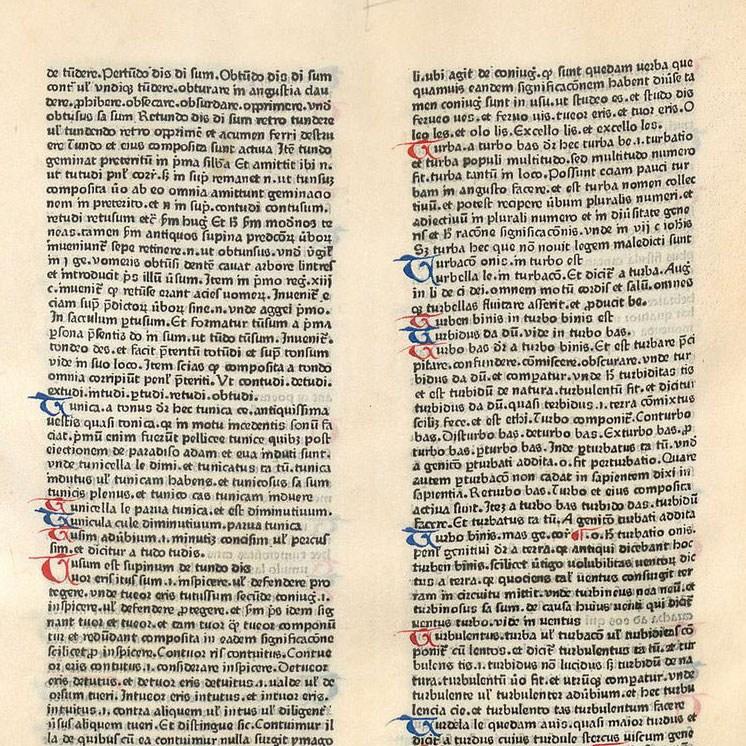
Ein klassischer Manuskripthalter für den Handsatz bestand aus einem Tenakel und einem Divisorium. Das Tenakel war ein Stück Holz, das über einen Metall-Sporn, einer Klemme oder einer Schraube am Setzkasten befestigt werden konnte.
Das Divisorium war ursprünglich eine Holzgabel, die entlang des Tenakels nach oben und unten geführt werden konnte.
Ein Durchbruch gelang dem Uhrmacher Ottmar Mergenthaler. Seine erste Maschine mit dem Namen »Blower« wird 1886 vorgestellt und kein geringerer als Thomas A. Edison bezeichnete sie ohne zu zögern als 8. Weltwunder. Zum Setzen des Textes bedient man sich bei dieser Maschine einer Art Schreibmaschinentastatur. Betätigt man eine Taste, wird eine so genannte Matrize – eine Gussform des Buchstabens – aus einem Magazin freigegeben. Der Setzer gibt nun so lange weitere Matrizen frei, bis eine Zeile gefüllt ist. Die komplette Zeile wird anschließend auf einmal gegossen und aus der Maschine ausgegeben. Dieses Prinzip gab der Maschine auch ihren Namen: A Line of Type (Eine Zeile Schrift). Kurz: Linotype. Die nach dem Guss nicht mehr benötigten Matrizen werden vollautomatisch in das Magazin zurückgeführt. Man kann somit ununterbrochen setzen und gießen und die Satzleistung eines geübten Setzers steigert sich durch diese Maschine auf circa 6000 Zeichen pro Stunde.
In Konkurrenz zur Linotype-Maschine wurde 1897 von Tolbert Lanston die Monotype entwickelt. Der Satz wird hier auf zwei Maschinen (und Berufe) aufgeteilt. Der Taster "setzt" auf dem "Taster", indem er ein papiernes Lochband "beschreibt". Dieser Lochstreifen steuert dann die Gießmaschine, die den Satz ausgibt: als korrekturfertige Kolumne aus Einzellettern (»Mono Type«) zusammengesetzt. So können eventuelle Tippfehler auch nach dem Guss noch leicht korrigiert werden. Es können auf einer Monotype-Gießmaschine aber auch Einzellettern zur Verwendung für Korrekturen oder den Handsatz gegossen werden. Es gab verschiedene Gießmaschinen für verschiedene Schriftgrößen. Die Monotype zeichnete sich durch eine bessere Qualität in der Zurichtung der Buchstabenpaare (am Computer Kerning genannt) und konnte auch größere Grade gießen (Linotype in der Grundausstattung nur bis 12p), brauchte aber mehr Platz, zwei verschiedene Spezialisten (Taster und Gießer), war im Betrieb deshalb teurer und die Matrizen konnten zeitweise/teilweise von der Monotype Corporation nur gemietet/geliehen werden.
Deshalb war die Linotype vorwiegend in kleinen und mittleren sowie in Zeitungsdruckereien sehr weit verbreitet, wogegen die Monotype zumeist in mittleren und großen Qualitätssetzereien zu Hause war. Es gab im 20. Jahhundert der Linotype-Setzmaschne technologisch sehr ähnliche und gleiche Lizenznehmer, Plagiatoren und Abwandlungen: in der Sowjetunion wurden beispielsweise die Rossija-Setzmaschinen gebaut, in den USA die Intertype-Maschinen.
Daneben gab es im 20. Jahrhundert auch noch die Setzmaschine "Typograph" (ebenfalls Ende des 19. Jahrhunderts erfunden). Diese erzeugte ebenfalls gegossene Zeilen, war aber ganz anders konstruiert als die Linotype. Der Typograph war kleiner und handlicher und kam vor allem in kleinen und kleinsten Druckereien zum Einsatz - sogar auf Ozeandampfern in dortigen Schiffsdruckereien!
Als Maschinensatz wurden gelegentlich auch Ludlow-"Maschinen" (und deren verwandte Ableger "Nebitype") bezeichnet. Das ist aber nicht richtig, weil auf diesen Geräten im Grunde nur von Hand im Winkelhaken gesetzte Matrizen abgegossen wurden und also nicht wirklich "gesetzt" wurde.
Handsatz und Maschinensatz auf der Linotype und Monotype waren die dominierenden Satzsysteme im beginnenden 20. Jahrhundert und wurden erst in den 1960er-Jahren zunehmend durch den Fotosatz und später das Desktop Publishing verdrängt.
Sind die verschiedenen Ziffernarten auf verschiedene Schriftschnitte verteilt, erkennt man die Mediävalziffern an dem Zusatz »OsF« (für Old Style Figures).
Aus dem Satztechnischen Lexikon: »Der Metteur ist die Seele des Blattes. Er ist oft die Mittelsperson zwischen Druckereigeschäft und Herausgeber; er muß der Redaktion wie auch der Druckereileitung mit Rat und Tat zur Hand gehen und angeben, wo etwas fehlt oder was von Nutzen sein kann. Der Metteur wird für die pünktliche Lieferung des Satzes verantwortlich gemacht, ob nun die Mitarbeiter ihre Pflicht erfüllen oder nicht.«
Multiple-Master-Fonts konnten sich nie auf breiter Front durchsetzen und werden heute selbst von Adobe, dem Entwickler des Formats, nicht mehr weiterentwickelt oder verkauft. Immer weniger Programme unterstützen sie daher.
Die Multiple-Master-Technologie wird heute vor allem noch von Schriftdesignern benutzt. Statt jedoch die variable Multiple-Master-Schrift selbst zu lizenzieren, werden typische Schriftschnitte auf Seiten des Schriftdesigners/Schriftanbieters gewählt und diese als reguläre Fonts ohne Eingriffsmöglichkeiten angeboten.
Kerbe A—Schriftgrad auf größerem Kegel (z.B. 9/10 p.) Kerbe B—Dreiviertelfetter Schnitt Kerbe C—Unterscheidungsmerkmal für Schriften mit ähnlichem Schriftbild (nach Wahl der Schriftgießerei) Kerbe D—Buch- oder Werkschriften wenn in der gleichen Schriftfamilie noch magere Schnitte vorhanden waren.
Dies führte jedoch dazu, dass die Grundlinien der Schrift nicht auf der gleichen Höhe lagen. Bei ausgefallenen Schriften, z.B. mit stark ausladenden Ober- und Unterlängen, war auch eine mittige Platzierung der x-Höhe nicht zweckmäßig (Abbildung rechts).
Beim Setzen war dies solange kein Problem, bis verschiedene Schriften in einer Zeile gemischt werden sollten. Anfang des 20. Jahrhunderts wurde deshalb die Deutsche Normalschriftlinie eingeführt. Sie wurde von der Hamburger Schriftgießerei Genzsch & Heyse nach dem Vorbild der Standard Line der Inland Type Foundry in St. Louis entwickelt.